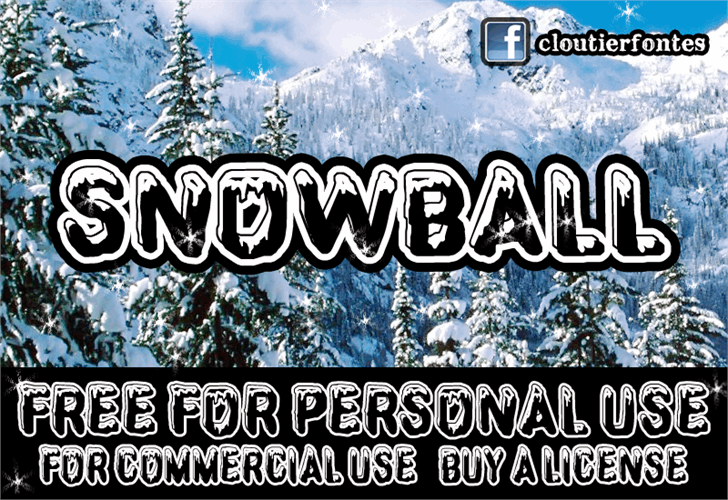
A CF SnowBall é uma fonte de exibição com estilo único que combina elementos suaves e modernos para oferecer um visual dinâmico aos projetos digitais. Desenhada pelo talentoso Hamilton, esta fonte foi criada para aqueles desejando uma abordagem mais alegre e vibrante em seus materiais impressos ou digitais. Com seu design assertivo e arredondado, a CF SnowBall é perfeita para destaque em logotipos, embutir em identidades visuais ou adicionar um toque de personalidade em texturas. Se você está procurando por uma fonte que se destaca, sem dúvida esta font será o seu candidato. Acreditamos que a CF SnowBall é perfeita para uso pessoal gratuito, seja para projetos da web ou impressão. Para usar na escala comercial, onde os detalhes adicionais e um grande número de caracteres são necessários, uma licença adicional precisa ser comprada. Esta fonte não só é bela e funcional, mas também permite aos designers adaptá-la ao seu próprio estilo criativo. É perfeito para aqueles que buscam um elemento alegre em suas criações digitais ou impressas. Sua versatilidade faz dela uma escolha ótima para projetos de marca personalizados, cartões de visita ou até mesmo ilustrações animadas. Sinta-se à vontade para experimentá-la e descubra o poder da CF SnowBall.